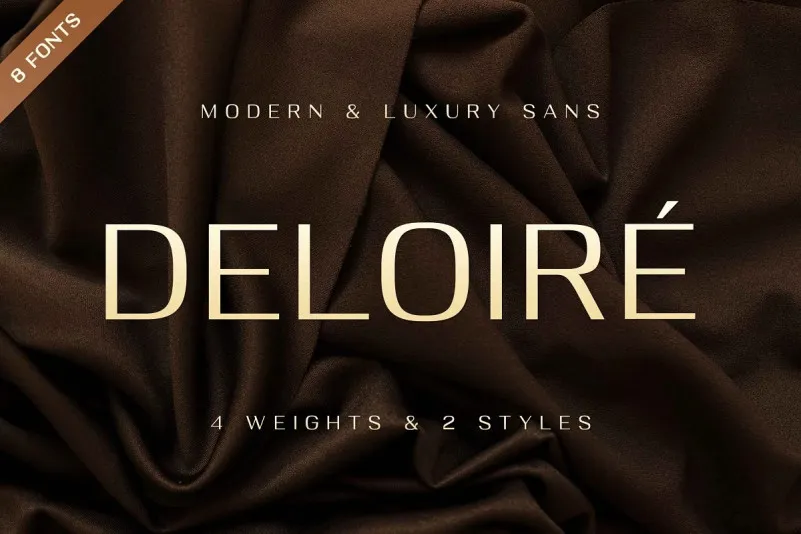
Deloire Font – Fonte Grátis
Deloire Font
A Deloire Font é uma tipografia sans-serif geometrica que oferece oito pesos diferentes, projetada para designers que buscam linhas claras e elegantes. Classificada como um famoso tipo de texto all caps display, Geometos Neue se destaca por sua simplicidade, agressividade aparente e clareza única. Seu design permite uma fácil leitura e combinação em diversos ambientes gráficos. Ideal para títulos em páginas de blog ou revistas, esta fonte é perfeitamente adaptada às necessidades do design moderno, oferecendo opções de texto variáveis que aprimoram sua estética visual e acentuam o impacto dos seus projetos. Seja você um designer profissional ou hobbyista, a Deloire Font é uma escolha conveniente para expressar seu trabalho em um ambiente digital cada vez mais sofisticado e funcional.